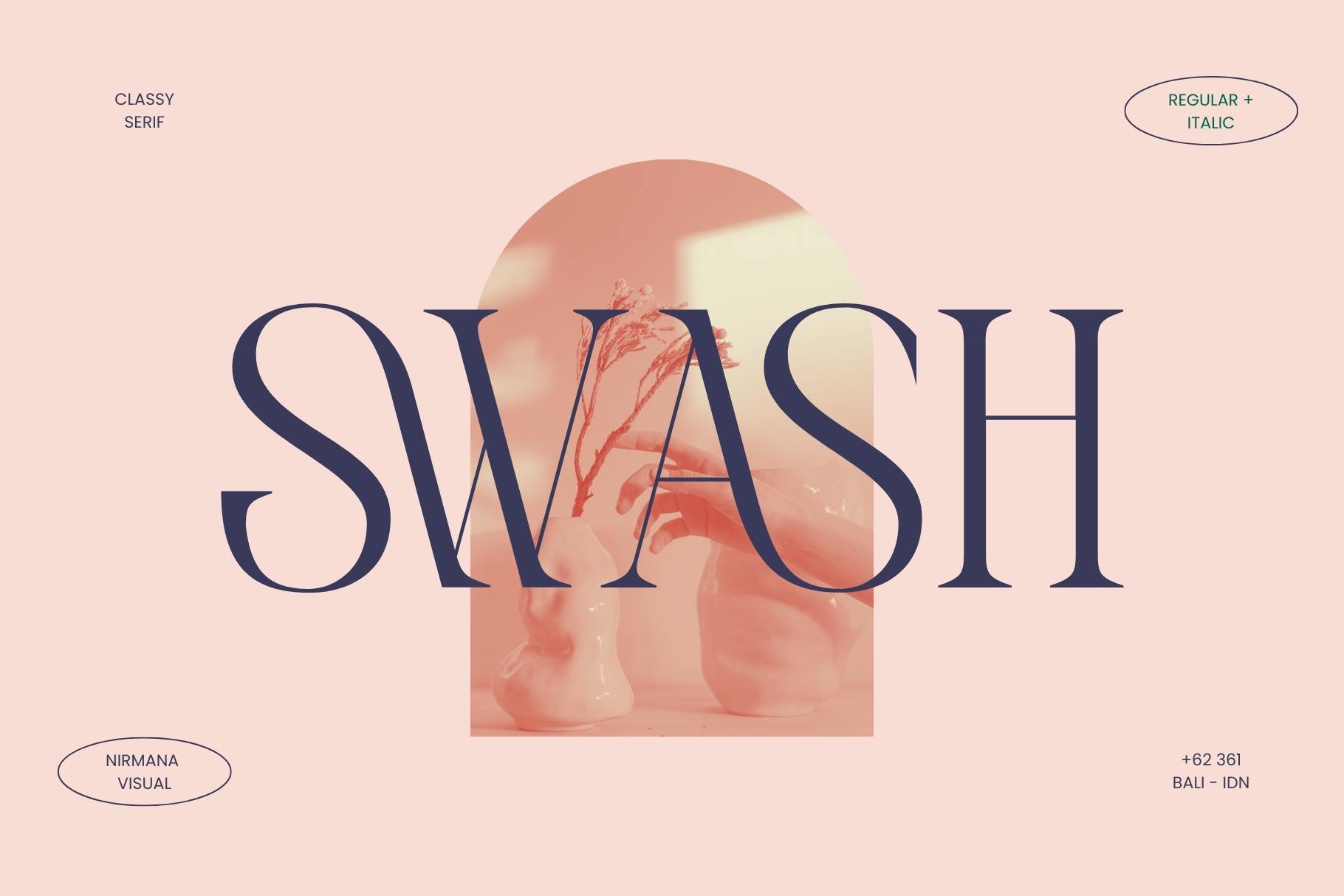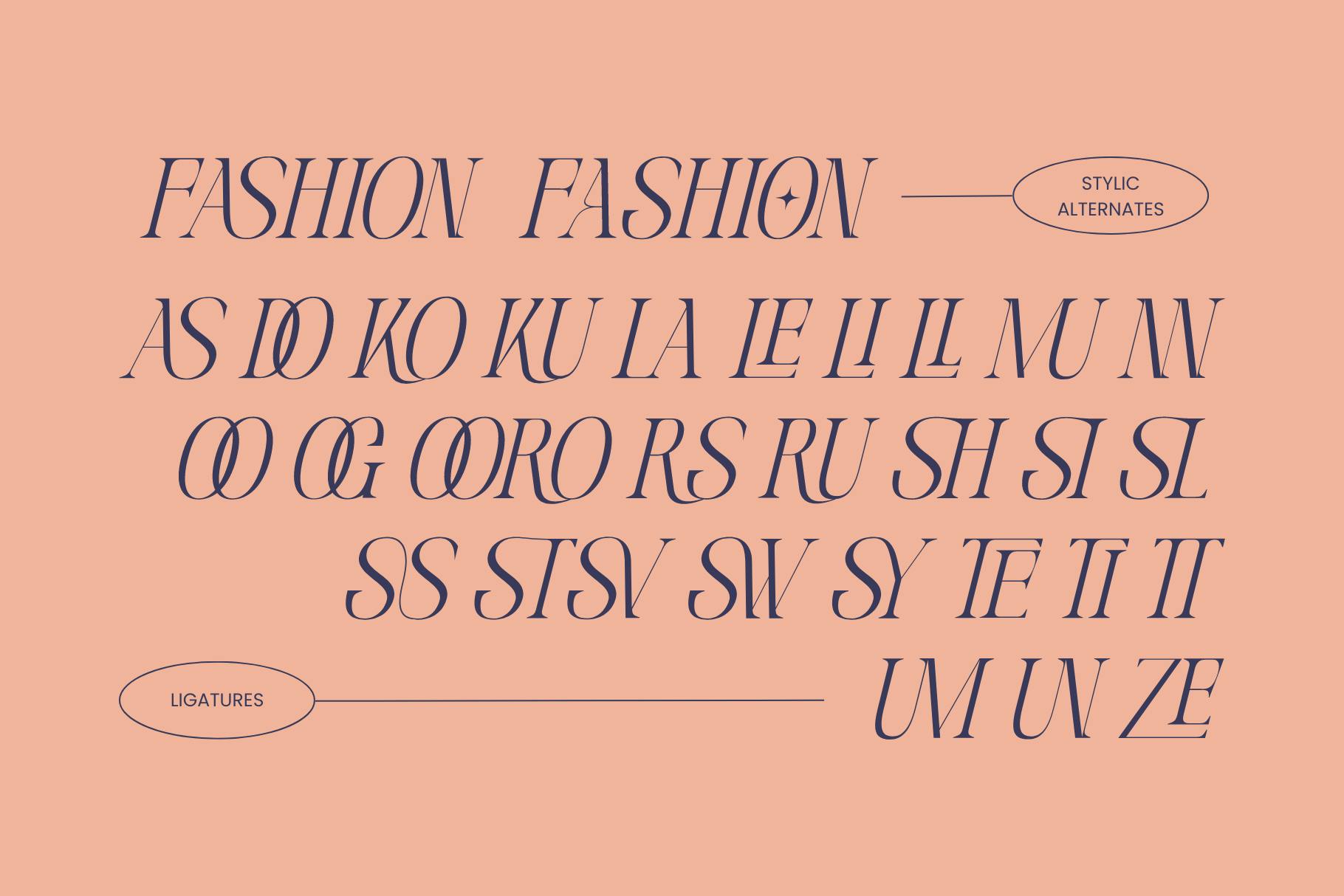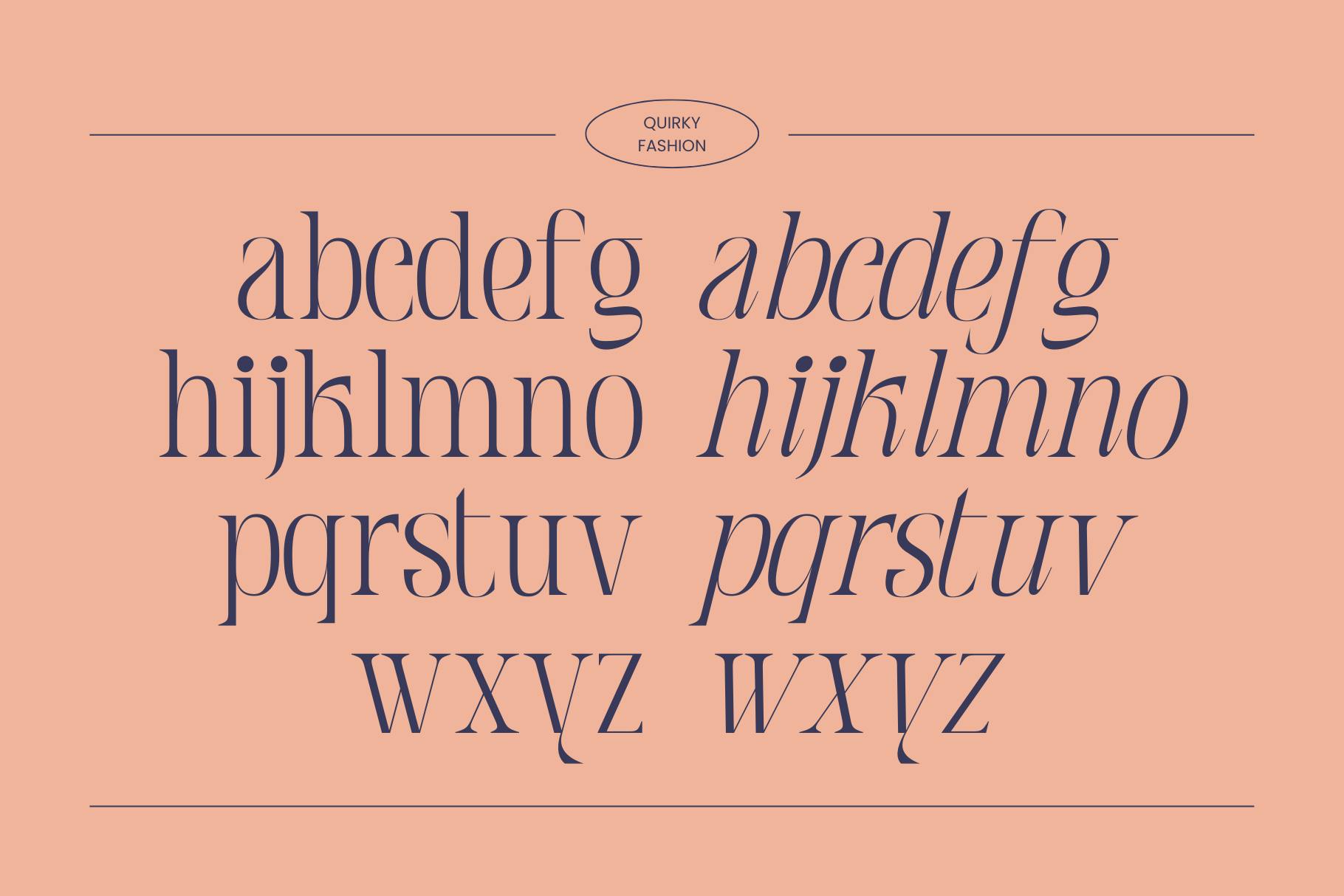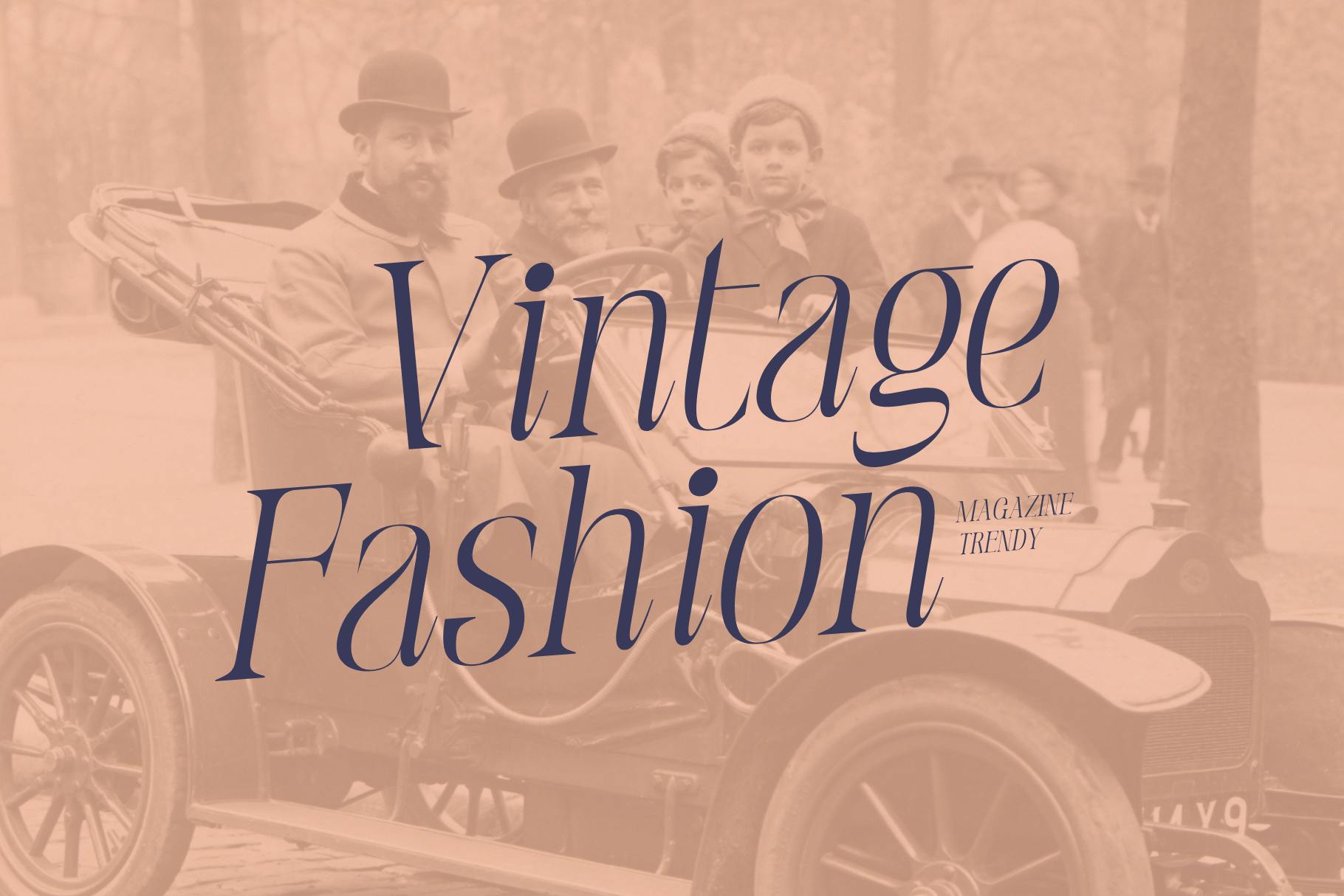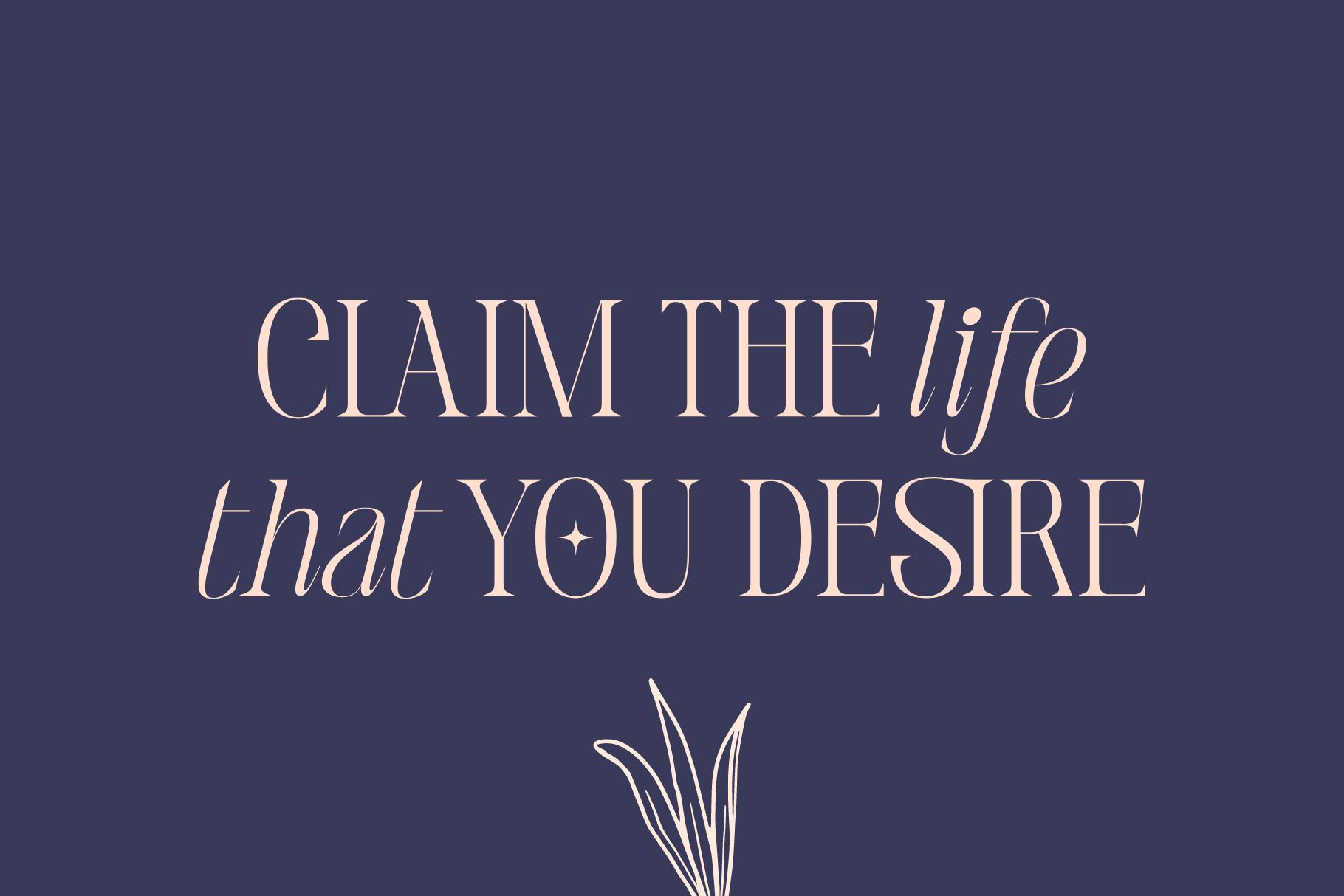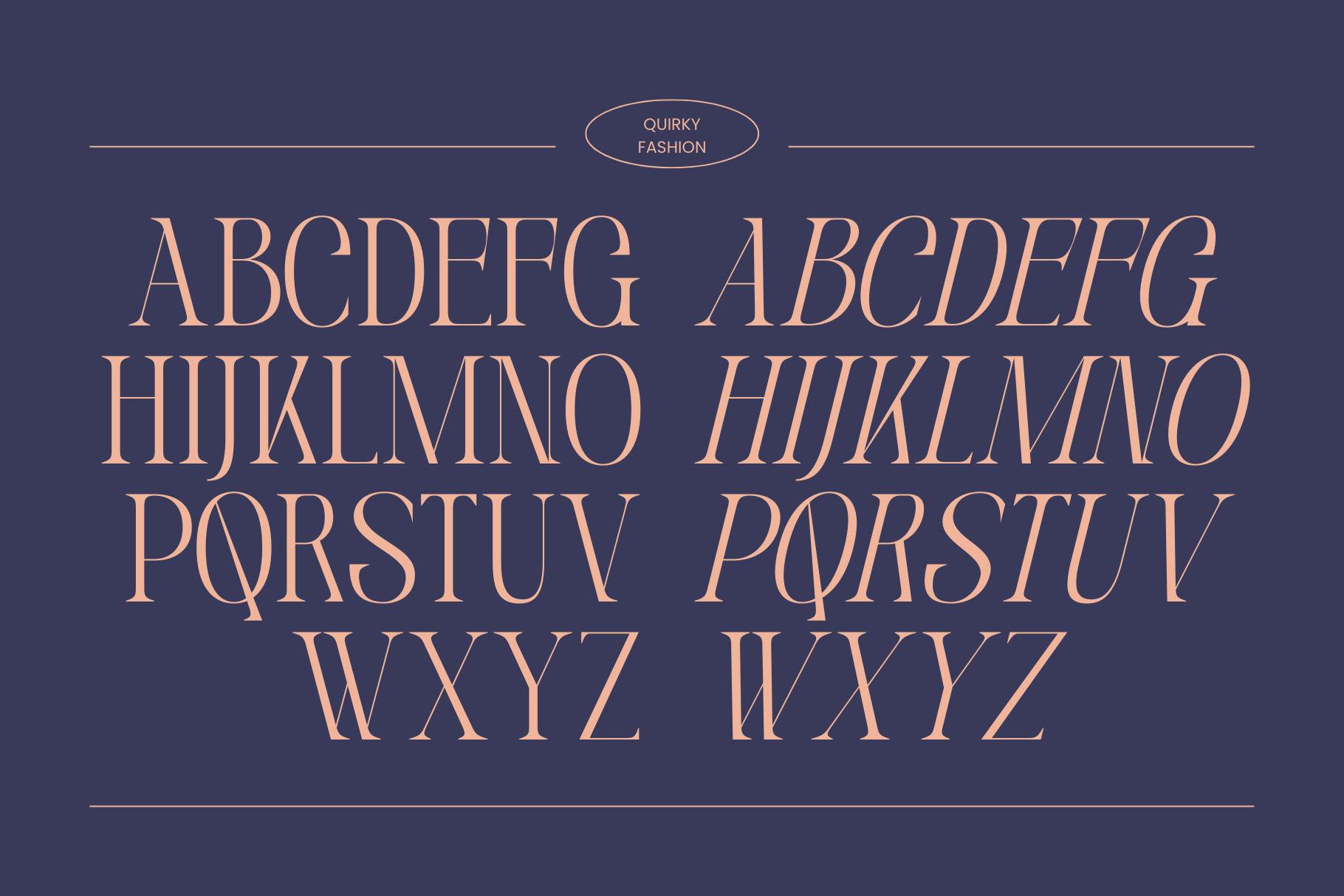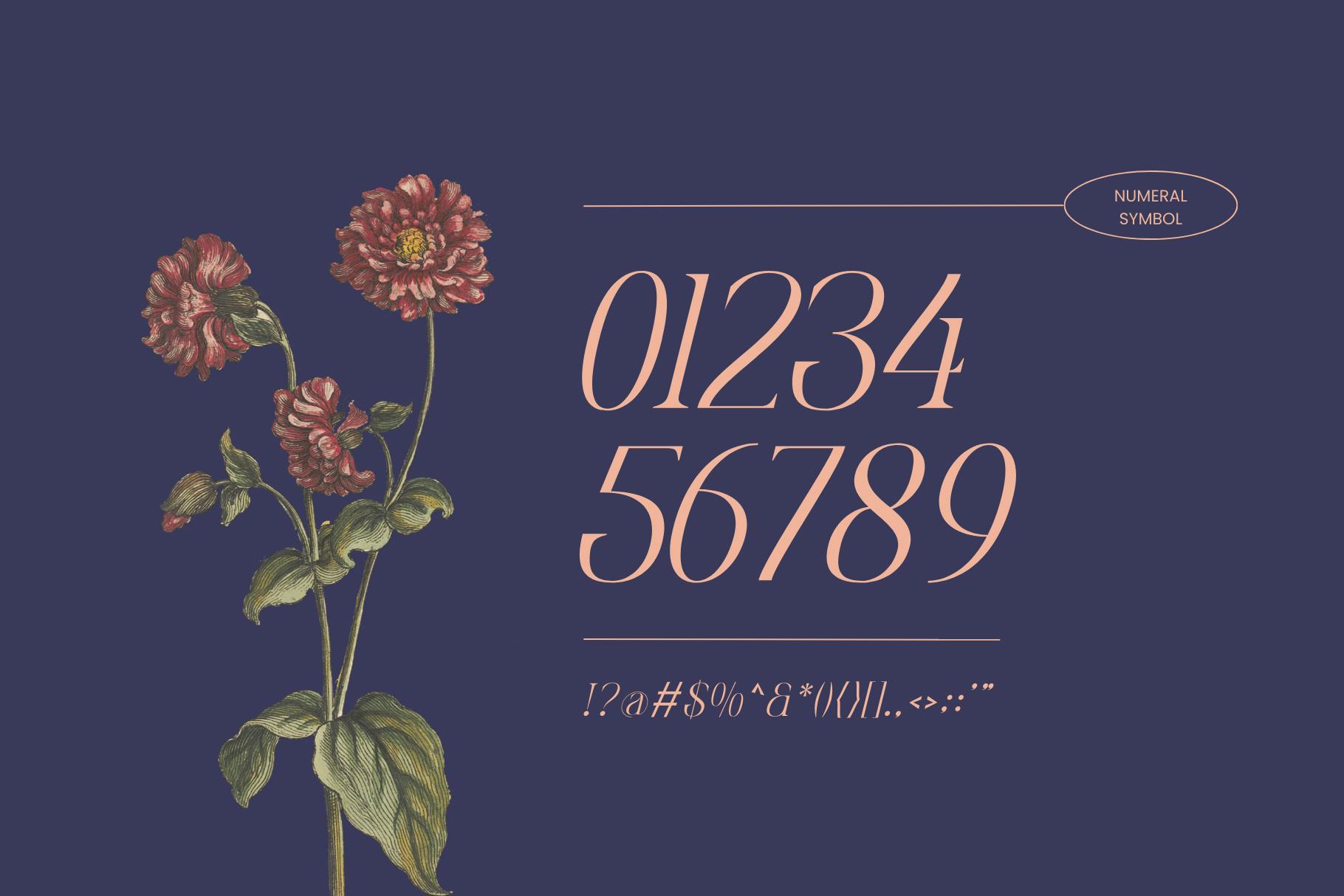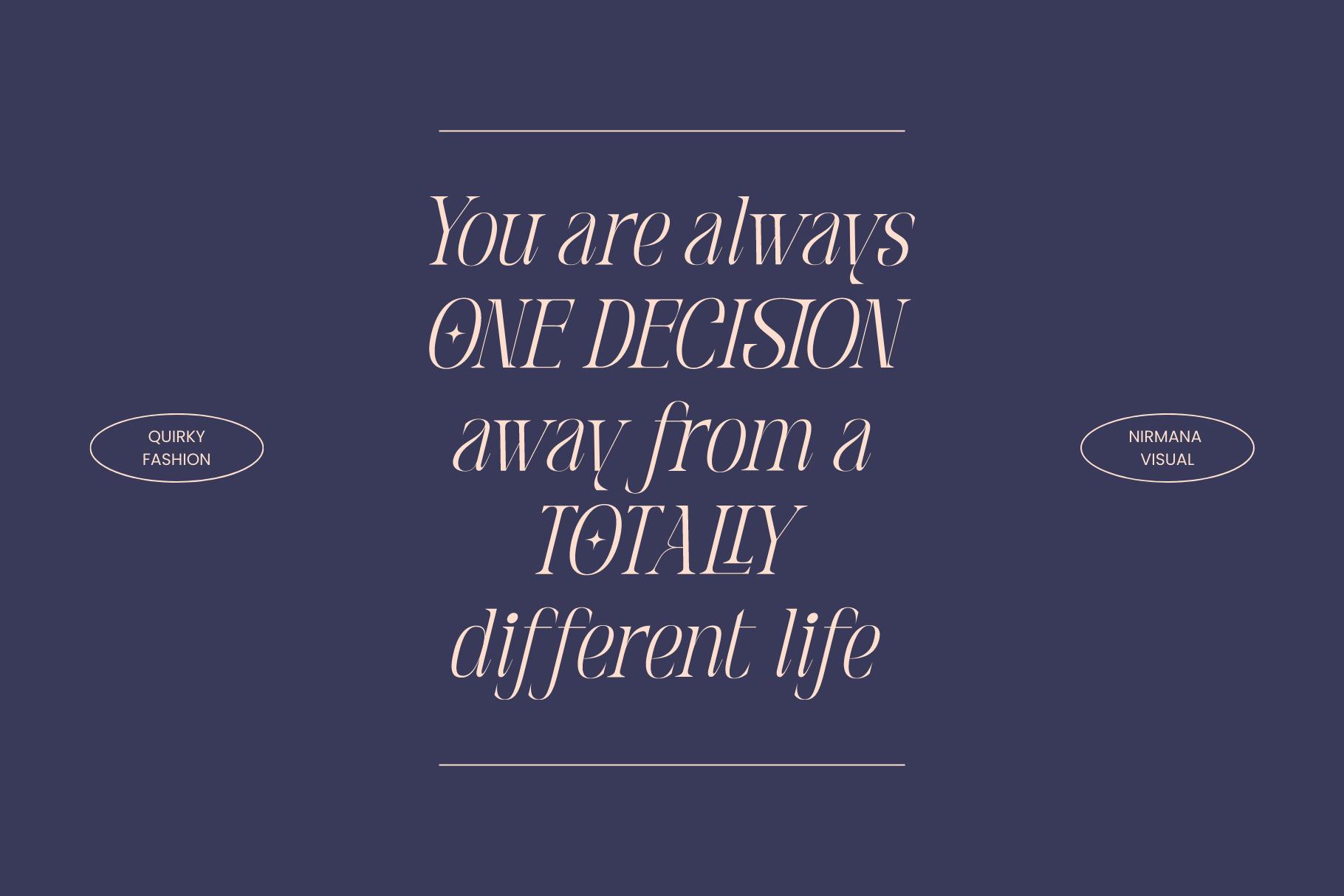
Quirky Fashion - فونت نمایشگر سریف.
فونت Quirky Fashion با دو استایل: Regular و Italic، هارمونی زیبای تایپوگرافی را برای تنوعی از پروژههای طراحی، از جمله لوگوها و برندینگ، پستهای رسانههای اجتماعی، تبلیغات و طراحی محصولات ارائه میدهد.